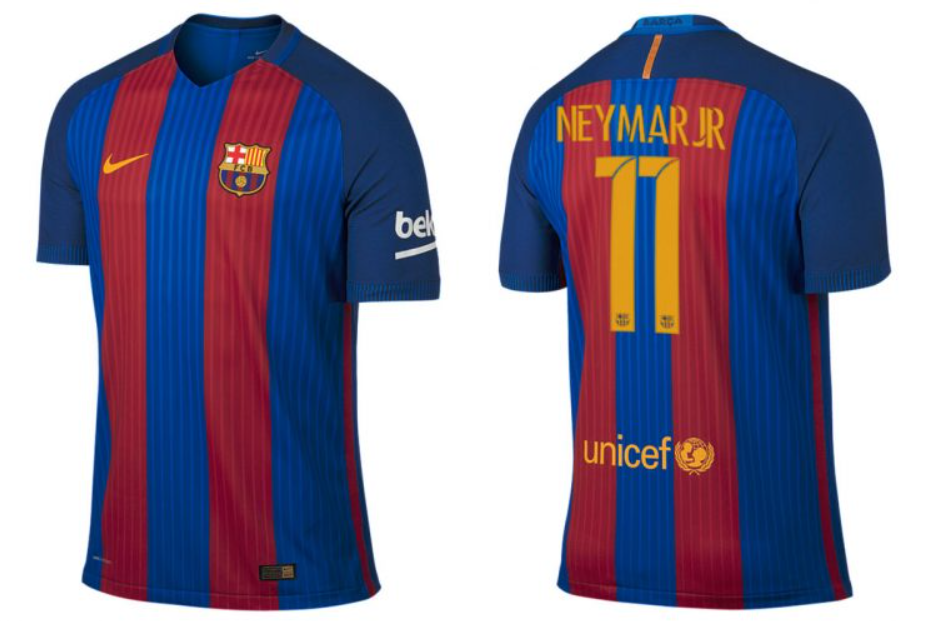
Se existe uma época que deixa saudade no torcedor do Barça e nos amantes do futebol arte, é a temporada 2015/2016. Foi o auge do trio MSN (Messi, Suárez e Neymar), e o uniforme daquela temporada entrou para a história não apenas pelos títulos, mas pela ousadia da Nike ao implementar as polêmicas listras horizontais no kit titular.
Este arquivo foi renderizado para garantir a máxima fidelidade aos números estampados nas costas dos craques daquele ano.
- Caracteres: Alfabeto completo e numeração oficial.
Estilo Visual e Identidade
A fonte desenvolvida pela Nike para a temporada 15/16 do FC Barcelona reflete uma modernidade agressiva. Fugindo dos estilos mais arredondados de anos anteriores, essa tipografia apresenta ângulos internos cortados e uma espessura (bold) que garante excelente visibilidade à distância.
Ela foi desenhada para contrastar tanto com o azul e grená do uniforme titular quanto com o amarelo vibrante (“Senyera”) usado na camisa reserva daquela temporada. É uma fonte que transmite impacto e velocidade, eternizada nas costas de lendas como Andrés Iniesta e Lionel Messi.